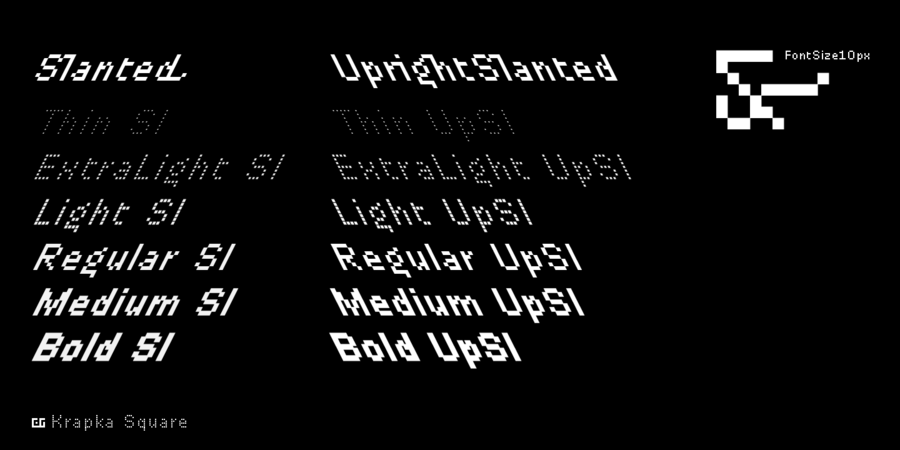
У цьому шрифтовому сімействі піксель має квадратну форму. Шрифт підтримує функції OpenType і містить капітель, лігатури, мінускульним цифри, дроби й індекси, історичні форми, стилістичні набори та розчерки. Також присутні символи, стрілки, і навіть емодзі. Для невеликих текстів рекомендується використовувати DR Krapka Square FontSize10px з розміром шрифту рівно 10 пікселів. Сімейство шрифтів DR Krapka Square підтримує європейські мови на основі латинки, кирилицю, в тому числі азіатську, і грецьку абетку. Якщо ви хочете використовувати шрифти з іншою формою пікселів, є й інші сімейства DR Krapka: DR Krapka Round (кола), DR Krapka Rhombus (ромби). Шрифт розробив Дмитро Растворцев у 2020 році.
Асоціації з сімейством шрифтів DR Krapka SquareОсобистість і характер гарнітури:
автоматичний, комп'ютерний, електронний, машинний, матричний, інженерний, байдужий, точний, гострий, різкий, тонкий, легкий, прозорий, невагомий, помітний, яскравий, чіткий, значний, впевнений, важкий, дивний, експериментальний, грайливий, робочий, грубий, рівний, квадратний, логічний, холодний, техногенний, твердий, стійкий, прямокутний, міський, урбаністичний, індустріальний, мужній, армійський, промисловий, незграбний, активний, суворий, брутальний, ігровий, тісний, чорний, потужний, швидкий, строковий, стрімкий, сміливий, рішучий, психоделічний, космічний, залізний, сталевий, спортивний, футуристичний, гоночний, енергійний, швидкісний
електроніка, автоматика, код, програмування, інженер, комп'ютер, робот, IT, айтішник, айті, андроїд, залізо, гра, фантастика, математика, технології, наука, хакер, рентген, комп'ютерна гра, лего, конструктор, цегла, іграшка, мультфільм, анімація, екскаватор, урбаністика, інструмент, промисловість, армія, завод, верстат, тара, склад, ремонт, депо, шолом, уніформа, вагон, автомат, шутер, екшен, страйкбол, будівництво, будматеріали, бойовик, сталевар, робочий, кубики, дискотека, аквадискотека, космос, гонки, ралі, формула 1, авто, тачки, спорт, авіація, літак, блокбастер, швидкість, кіберспорт, супергерой Гарнітура має ознаки стилів: